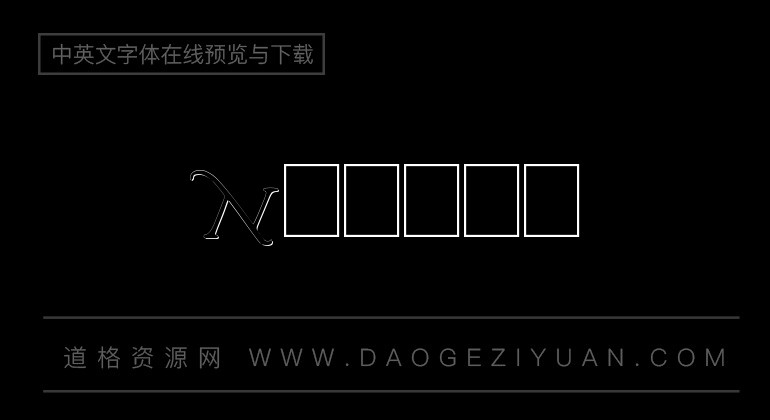
Nauert是一种西方书法风格的字体,它的风格受到了文艺复兴时期书法家尼古拉斯·朗基斯特(Nicolas Jenson)的启发。Nauert字体采用了古典的比例和优美的曲线,使得它在正式场合和文艺复兴风格的设计中都非常适合使用。 Nauert字体的特点是线条流畅、笔画精细、形态优美,适用于印刷、排版和文本设计。它非常适合用于书籍封面、标题设计、宣传手册、特色海报等需要凸显文艺复兴时期风格的设计中。 Nauert字体由制作字体的专业设计师Robert Slimbach于2004年设计,最初发行于Adobe公司的字体库中,并且现在可用于Adobe软件、Microsoft Office等广泛应用的软件中。内容介绍
Nauert是一款非常不错的手写艺术字体,具有很好的视觉感,适合于文化类的宣传设计、商业类品牌的广告和产品包装设计以及个性化文字排版等较多场景。